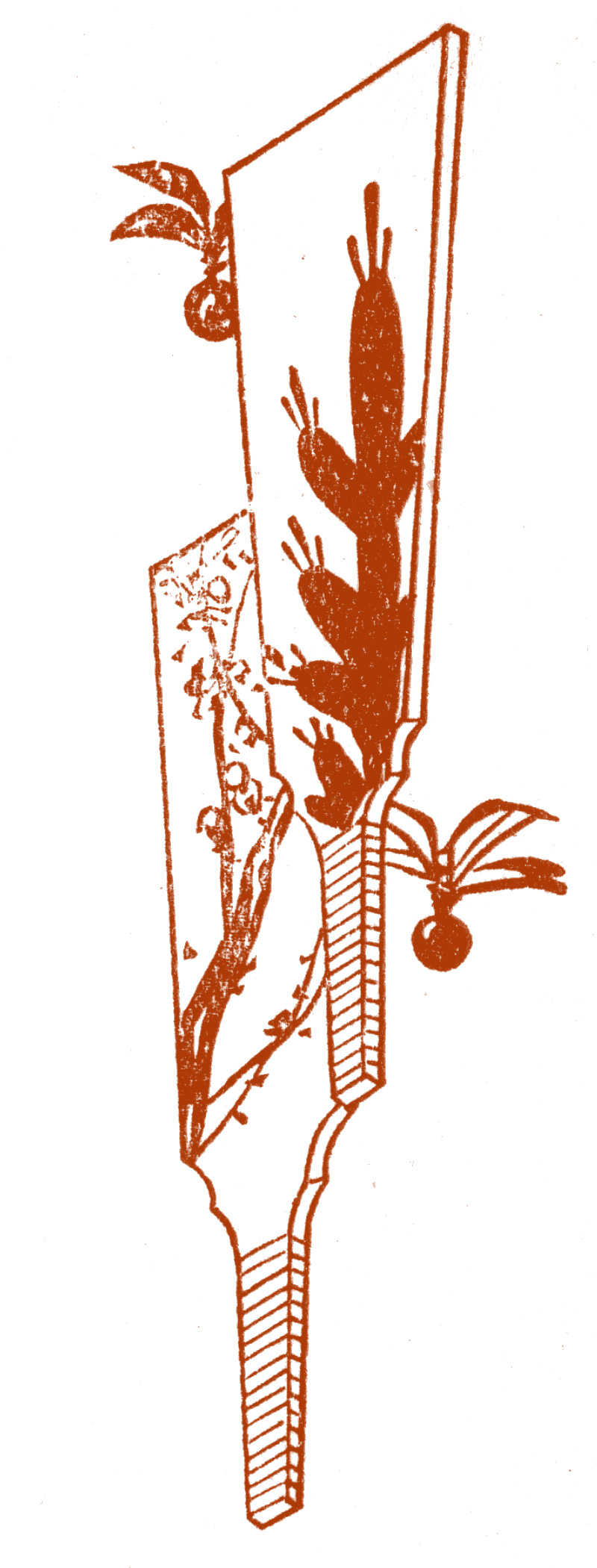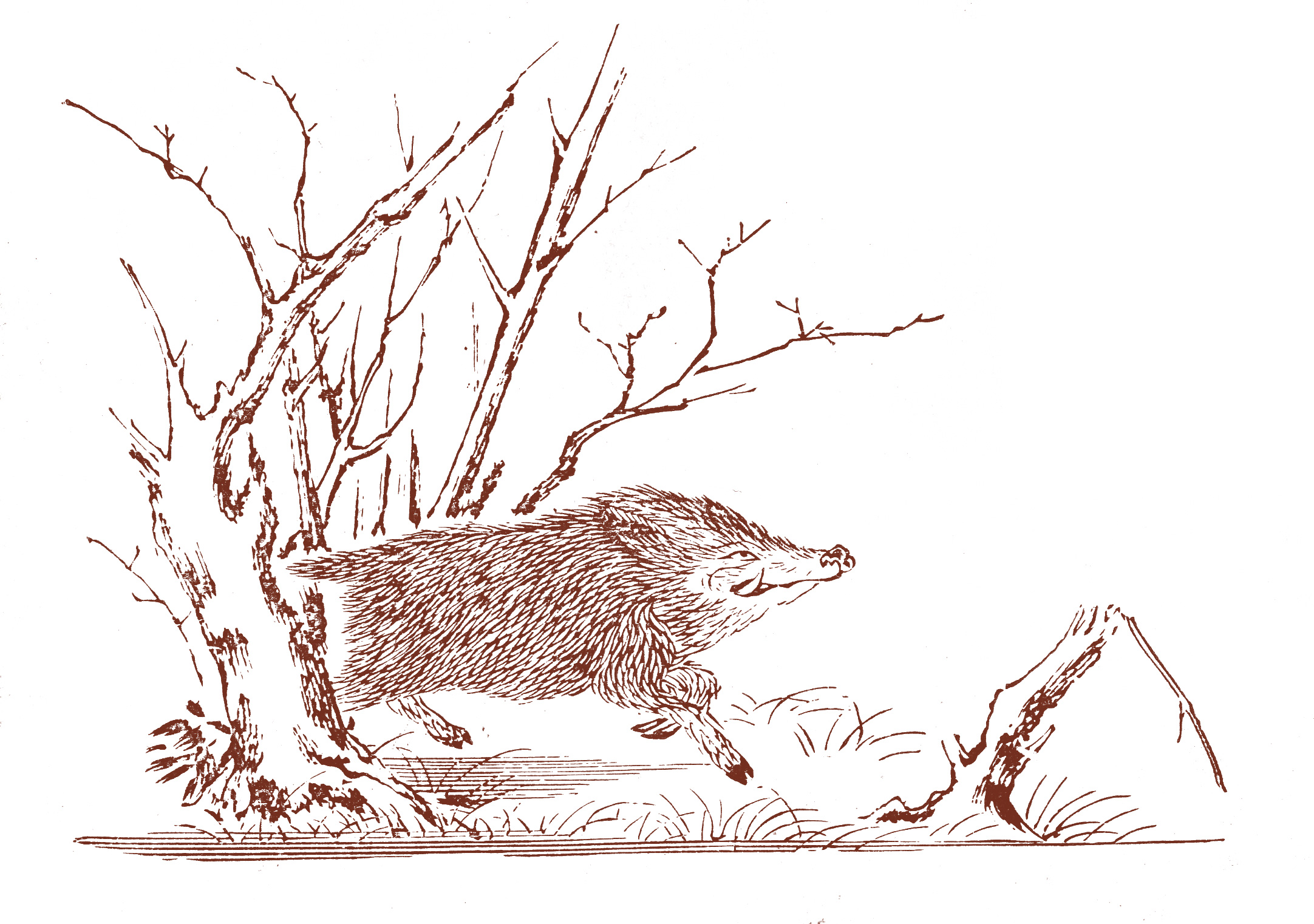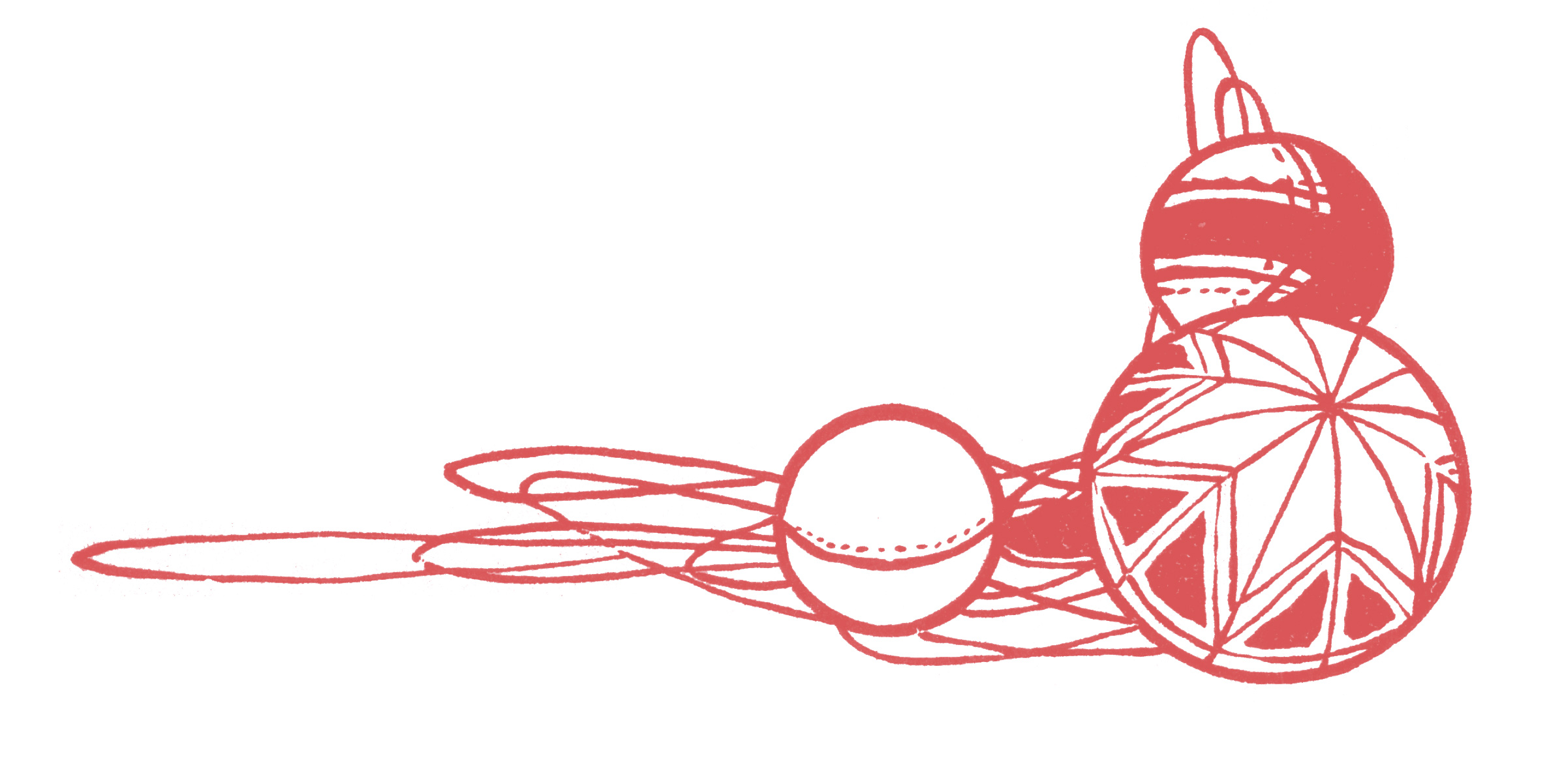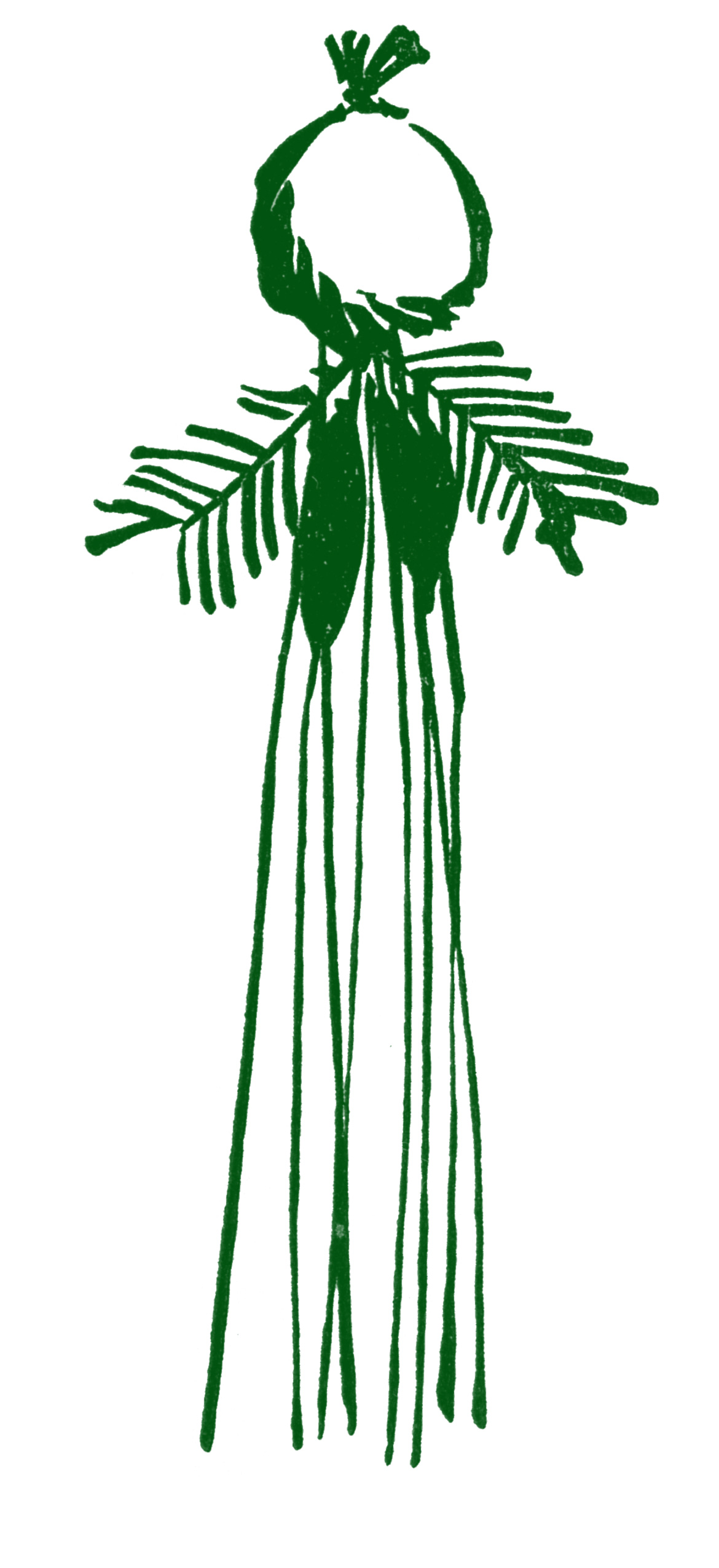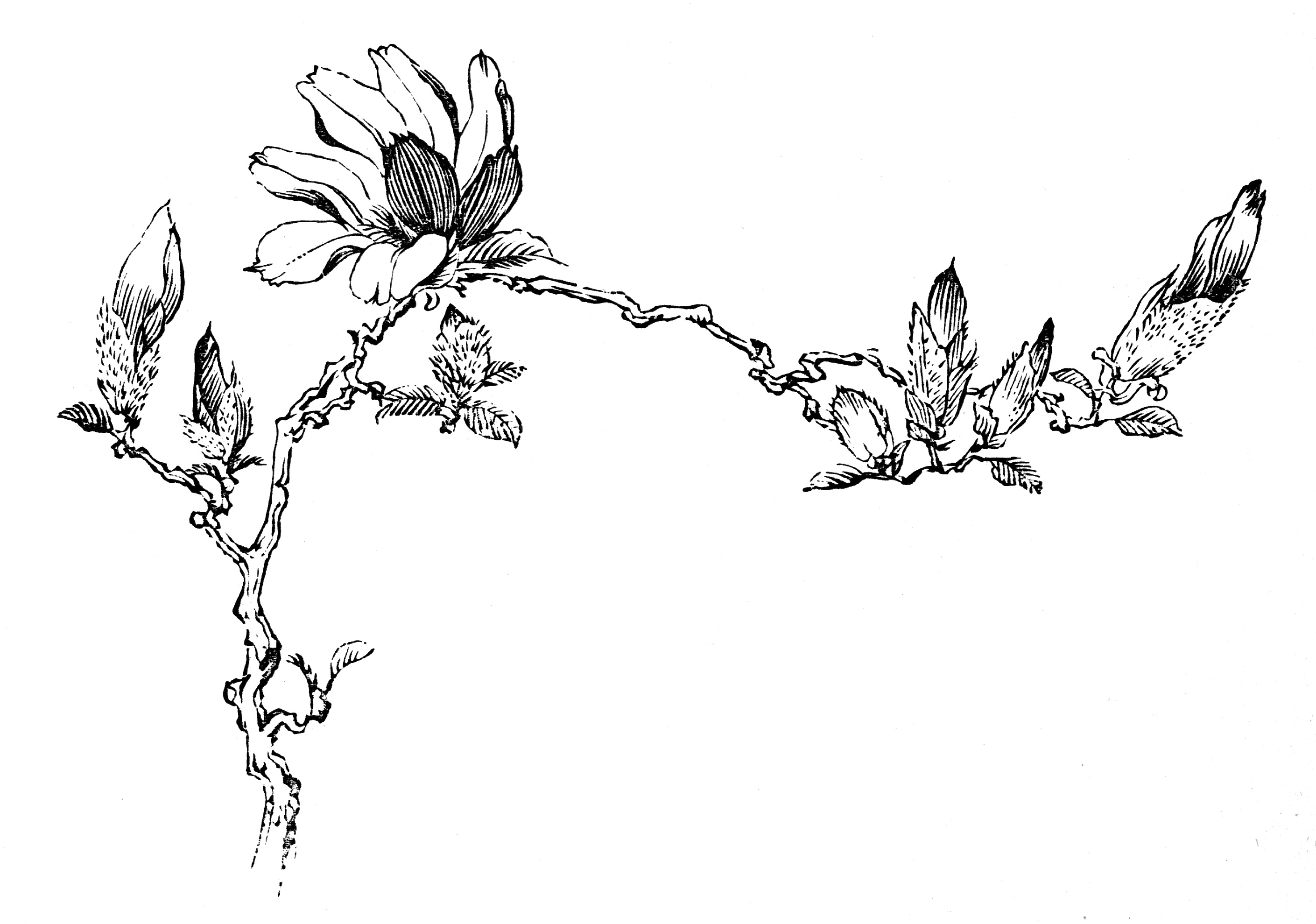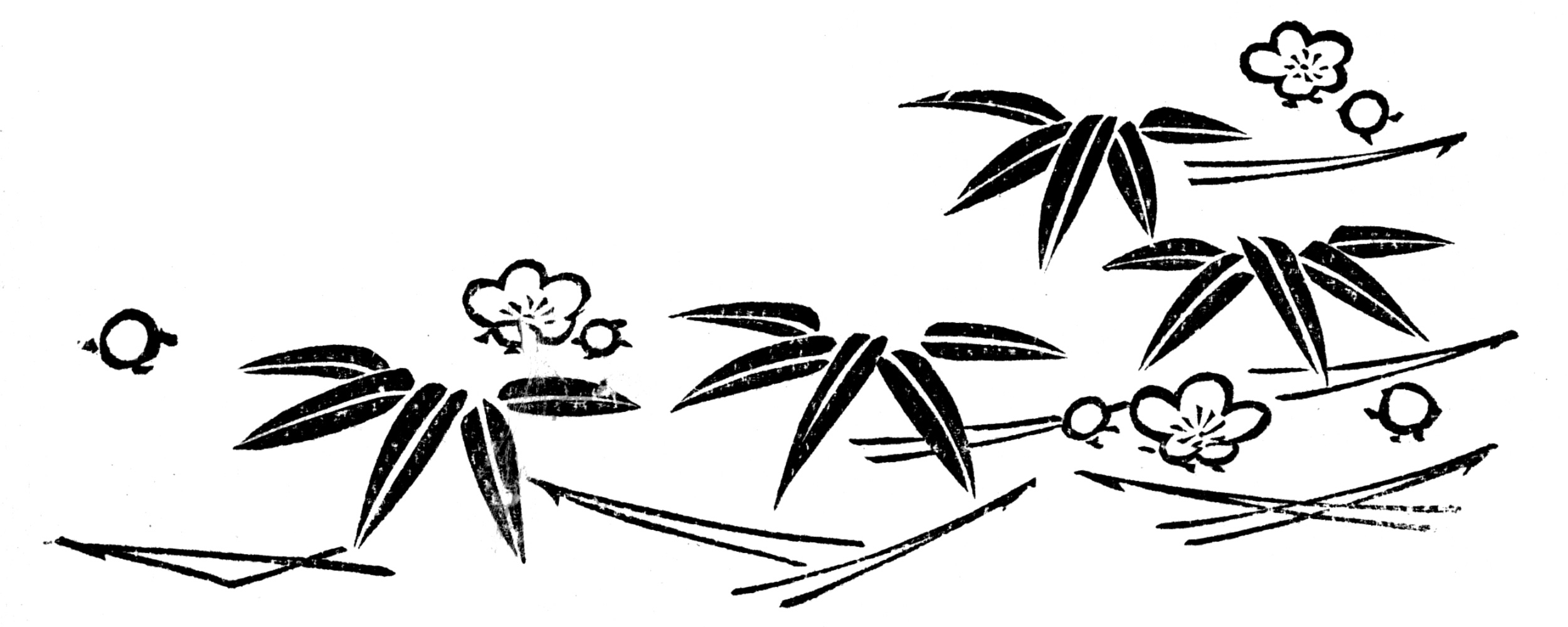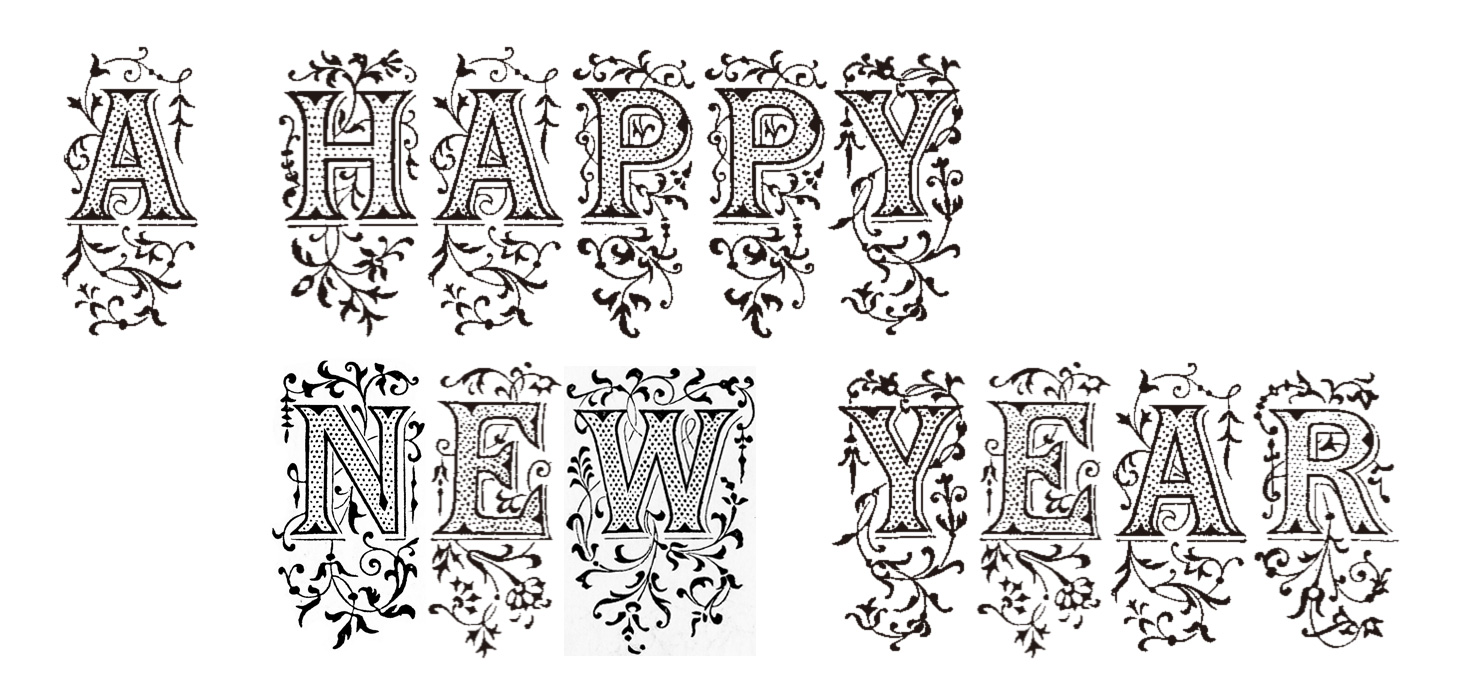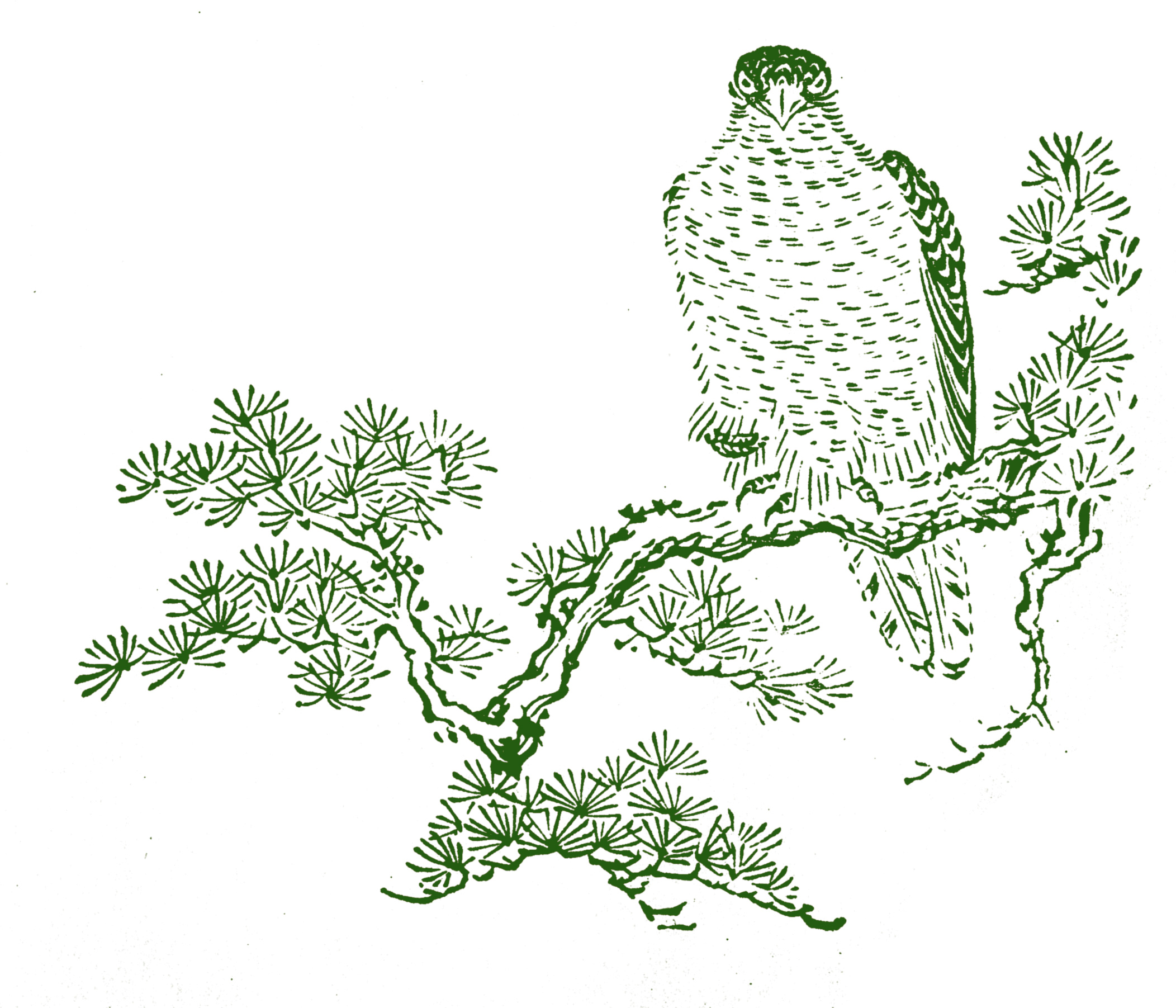
第21回 2006年も大正3年『活版見本帖 Type Specimens』から年賀状を作ろう!
今回の秀英体のコネタは、一年間のご愛顧に感謝いたしまして、秀英舎・大日本印刷が誇る最大規模の見本帳、大正3年版『活版見本帖 Type Specimens』から、来年の干支であるいのししや冬・新春らしい柄などをピックアップいたしました。
まだ年賀状を作っていない方、昨年の「第14回 大正3年『活版見本帖 Type Specimens』から年賀状を作ろう!」と併せ、ぜひご活用ください!
2007の干支、いのしし集合! といきたかったのですが……
来年の干支はいのしし。というわけで見本帳をなめるように探したのですが、昨年の犬とはうって変わって、いのししがいません! いのししは干支ぐらいでしか出版物には登場しないようです。
しかしキュートないのししも発見しました。
来年を飾る3頭のいのししたちです。
枯木立を駆け抜けるいのししです。足取り軽やかに、2007年を駆け抜けます。
ほのぼの系のかわいらしいいのししです。
こちらは少しきりりと。木版画のような線の味わいがあります。
お正月らしいおめでたい絵柄
羽子板もお正月らしいイメージですよね。
お正月のお飾りも準備しないといけません。
初夢縁起のひとつにも数えられる鷹も、年賀状にはうってつけです。
冬の厳しい寒さをものともせず緑と花をつける歳寒の三友・松竹梅は、おなじみのめでた柄です。
新春柄、そして仲良し柄
冬の食材として、そしておせち料理にも使われる大根とくわい。素朴な年賀状にどうぞ。
手毬は江戸時代から戦前まで、女の子のお正月遊びの定番だったそうです。
まだ寒いうちからつぼみをつけるたんぽぽは春の顔です。
すくすく伸びるつくし。うららかな春を思わせる絵です。
木蓮も春を告げる花。ふわふわした産毛に包まれた芽もかわいいですよね。
梅と一緒の登場が多い鶯ですが、こちらは菜の花と。
寒そうに羽根をふくらませたうずら。二羽で仲良く身を寄せ合います。
少しヨーロッパの香りのするつがいの鳩。ご夫婦の年賀状にいかがでしょう。
「あけましておめでとうございます」を秀英体で!
絵が決まったら、ご挨拶のテキストです。
大正3年『活版見本帖 Type Specimens』に掲載されている SIX-LINE PICA ELECTRO ORNAMENTED で「A HAPPY NEW YEAR」をどうぞ。
こちらは秀英舎の古い見本帳に掲載され、現在も市谷工場の母型庫に鋳造された活字も残っています。明治期に海外から輸入したか、秀英舎内で作ったものかは定かではありませんが、100年以上秀英体とともに一緒にいた欧文活字です。
アルファベットに植物の飾りがついた豪華な書体です。
そして絵に添えることばをぜひ秀英体で!
まずは昭和4年発行の『明朝初号活字見本帳』より秀英初号の漢字です。
写植をご存知の方であれば、写研の「秀英明朝 SHM」としておなじみの秀英初号。SHMの開発も、この昭和4年の見本帳を元に進められたそうです。
秀英体最大サイズとして、タイトルや見出し用途で開発されたその形は、安定感のある引き締まった線質が特徴です。
年賀状では明朝体を使うことはあまりないですが、
この「謹賀新年」はかなりきりりとした表情になりますよ。
続いては仮名で、秀英初号と秀英細明朝体です。
この2書体、昨年も同じように登場しましたが、実は今年の文字は昨年のものとはひと味違います。どう違うか詳しくはまだご報告できないのですが、コネタをご覧頂いているみなさまに特別にご紹介する最新の秀英体です。
あっという間の2006年も、さまざまなかたちで秀英体をご紹介することができました。
書籍や雑誌だけでなく、街角の看板や広告物での使用もありました。また、ハイビジョンアーカイブやDVDの表示用字幕としての使用も、少しずつですが生まれてきた年となりました。
東京国際ブックフェアでの直彫り・ゲラ刷りの実演は、たくさんのご来場を頂いただけでなく、大きな反響もありました。忘れられない思い出です。
来年も、秀英体の取組みをご紹介してまいります。2007年も秀英体をよろしくお願い致します。